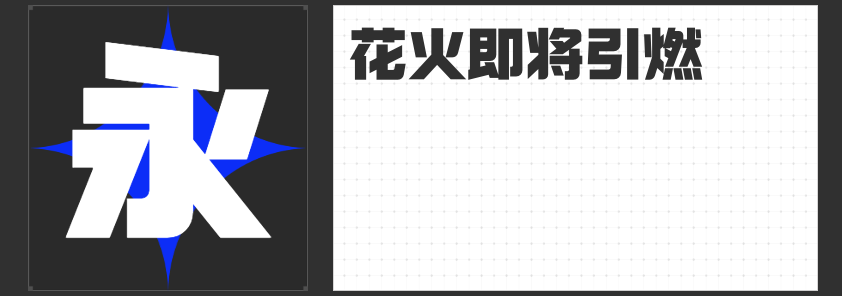
超粗创意黑体,让设计更具视觉冲击力
在设计的世界中,字体不仅是文字的载体,更是传达情感和理念的重要元素。今天,我要向大家推荐四款专为设计而生的超粗创意黑体字体——励字开拓者简特级黑、励字铁拳简超级黑、励字勇敢黑简超黑和励字造梦简大粗。
以其方正的字型和适中的重心,展现出一种简约而不失力量的美感。这款字体全部采用直线笔画,横平竖直,棱角分明,起笔和收笔以平切为主,使得整体平衡而富有节奏感。特别值得一提的是,它包含了诸如“又、双、叒、叕、囍”等网红流行用字,让设计作品更加贴近潮流,充满趣味性。
则是一款视觉冲击极为强烈的创意黑体字。笔画粗壮,字面宽大,饱满的块面感与折角圆设计相结合,犹如铁拳出击,横扫千军,为设计作品带来无与伦比的震撼力。
以其无衬线装饰、笔划粗壮有力的特点,成为标题、导语和标志设计的首选。撇捺等笔画不尖,横直均匀,使得字体突出醒目,易于阅读,同时又不失艺术感。
四、励字造梦简 大粗
则是一款充满青春活力的字体。其设计灵感来源于“青春筑梦”,左侧倾斜右侧竖直的不对称设计,夸张的透视感模拟了建筑的宏壮,让人仿佛在城市之中抬头仰望摩天大厦。这款字体直线型设计,有力量感,棱角分明,字形轮廓清晰有力,是展现创意与激情的绝佳选择。
这四款超粗创意黑体字体,各具特色,无论是用于海报设计、广告宣传还是品牌标识,都能为作品增添独特的视觉魅力。如果你正在寻找能够提升设计质感的字体,不妨试试它们,相信你会有意想不到的收获。